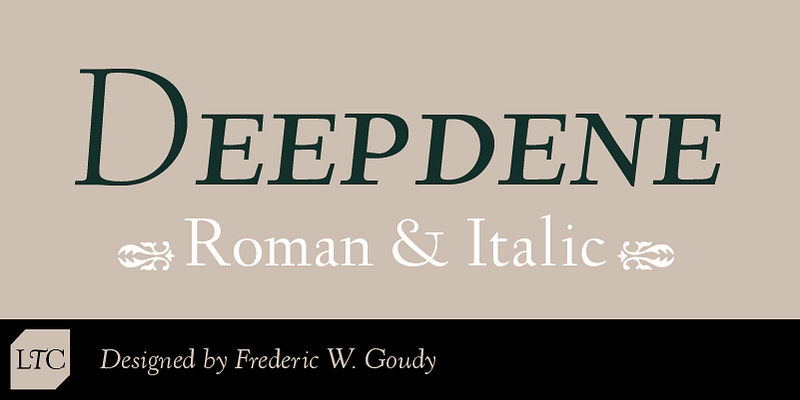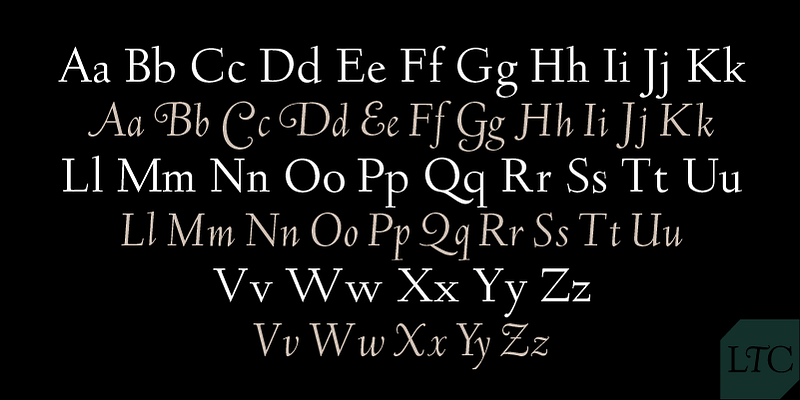
Les origines de la société Lanston Type Co. (LTC) remontent à la Lanston Monotype Company établie en 1887 par Tolbert Lanston, l’inventeur de la fondeuse Monotype. Après la séparation d’avec sa partenaire anglaise, LTC a connu des difficultés et a été rachetée plusieurs fois par American Type Founders, Hartzel Machine Works, Mackenzie & Harris, puis Gerald Giampa. Finalement reprise en 2004 par P22 Type Foundry, elle abrite désormais les créations classiques de Frederic W. Goudy et Sol Hess, ainsi que des nouveaux maîtres contemporains Giampa, Jim Rimmer et Dave Farey.